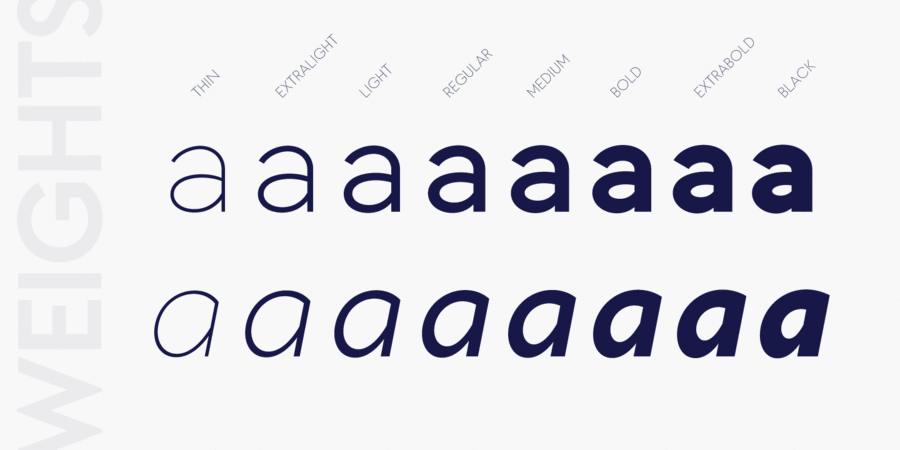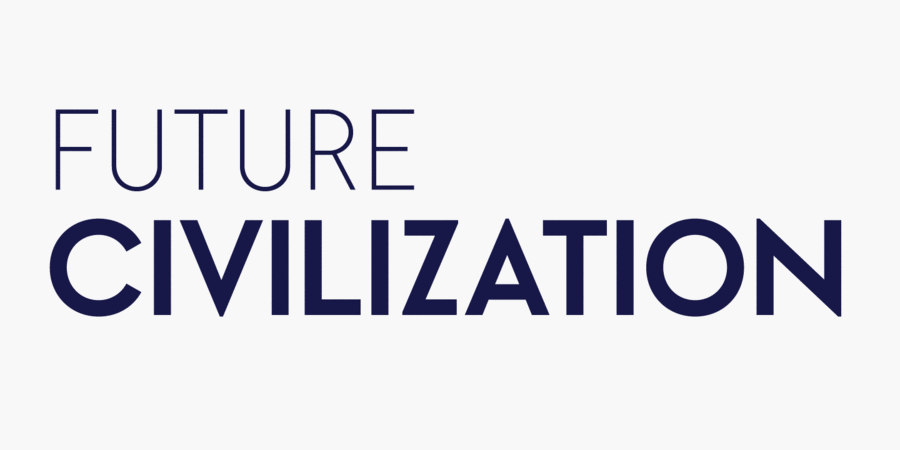
Geraldton – це теплий і доброзичливий геометричний ґротеск у 8 насиченостях з відповідними курсивами. Його мала висота рядкових літер і гострі кути навіяні геометричними шрфітамі 1920-х і 1930-х років і доповнені легким сучасним гуманістичним відтінком. Він підтримує всі європейські мови на латиниці, а також кирилицю. Крім того, Geraldton має численні функції OpenType і містить десятки символів комп'ютерної тематики. Шрифт розробив Олег Ліщук у 2020 році.
Асоціації з сімейством шрифтів GeraldtonОсобистість і характер гарнітури:
гострий, круглий, трикутний, дзвінкий, чистий, твердий, позитивний, якісний, модний, популярний, гладенький, точний, лаконічний, холодний, невагомий, легкий, прозорий, худий, ясний, скляний, крихкий, дротяний, сучасний, міський, неоновий, ввічливий, динамічний, свіжий, дорогий, багатий, зрозумілий, радісний, святковий, добротний, здоровий, щасливий, грайливий, прикольний, яскравий, помітний, важкий, щедрий, активний